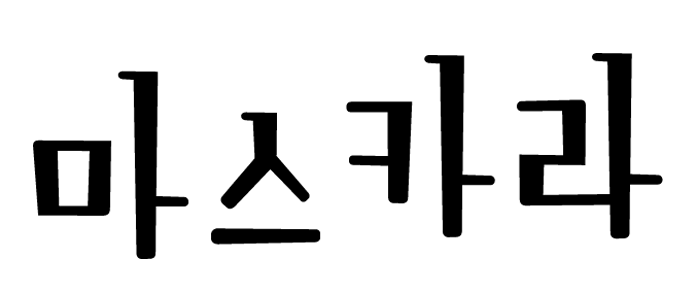
Sandoll 마스카라
산돌 마스카라는 좁은 글자 폭이 엣지있고 세련되게 느껴지는 폰트이다.
날씬하다는 느낌까지 드는 좁은 글자 폭은 세련된 신세대 여성의 모습을 연상시키며 글자마다 강조된 세리프는 마치 진한 마스카라로 화장한 것도 같다.
가로획과 세로획 굵기에 차이를 두어 단조로울 수 있는 디자인에 변화를 주었다.
Sandoll 마스카라